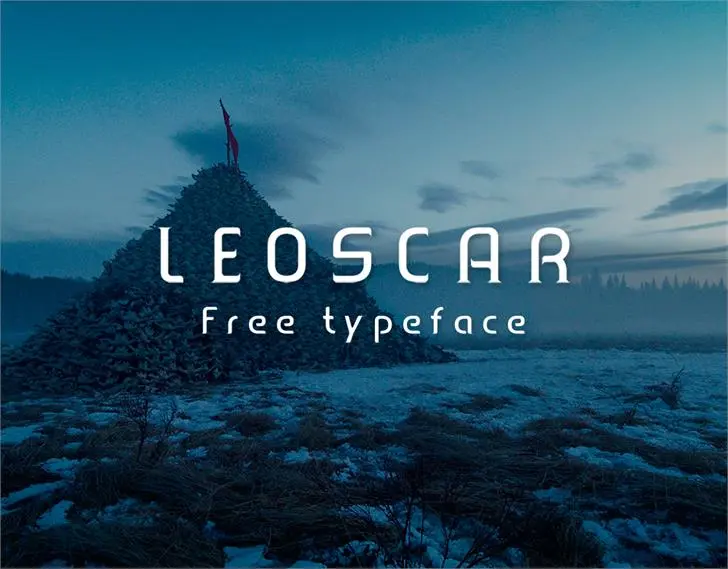
Leoscar font – Download Grátis
A Leoscar é uma nova tipografia moderna desenvolvida em um curso acadêmico sobre Multimídia e Tecnologia Criativa na Daffodil International University. Inspirada no trabalho de alunos talentosos, a Leoscar busca capturar o espírito contemporâneo e a simplicidade que tanto fazem sucesso na era digital. Agradecemos especialmente ao nosso professor de carinho, Senhor Abu Kalam Shamsuddin, por sua orientação incansável e visão clara sobre o design tipográfico. Como uma fonte do tipo Sans Serif, Leoscar oferece um visual limpo e funcional para diversos usos, seja em projetos digitais ou impressos.